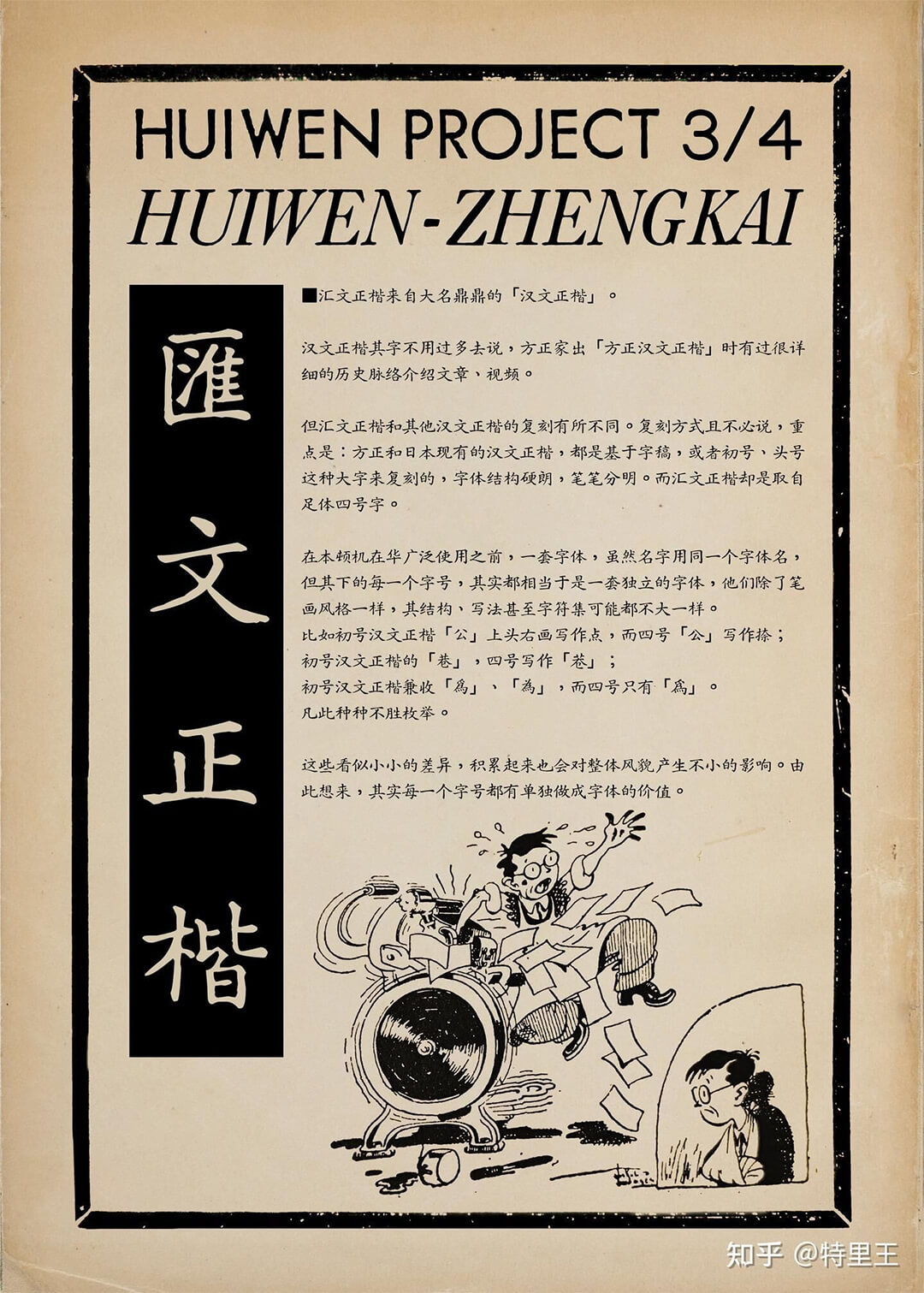
汇文正楷来自大名鼎鼎的「汉文正楷」。
汉文正楷其字不用过多去说,方正家出「方正汉文正楷」时有过很详细的历史脉络介绍文章、视频。
但汇文正楷和其他汉文正楷的复刻有所不同。复刻方式且不必说,重点是:方正和日本现有的汉文正楷,都是基于字稿,或者初号、头号这种大字来复刻的,字体结构硬朗,笔笔分明。而汇文正楷却是取自足体四号字 。
在本顿机在华广泛使用之前,一套字体,虽然名字用同一个字体名,但其下的每一个字号,其实都相当于是一套独立的字体,他们除了笔画风格一样,其结构、写法甚至字符集可能都不大一样。
比如初号汉文正楷「公」上头右画写作点,而四号「公」写作捺;初号汉文正楷的「巷」,四号写作「巷」;
初号汉文正楷兼收「爲」、「為」,而四号只有「爲」。
凡此种种不胜枚举。
这些看似小小的差异,积累起来也会对整体风貌产生不小的影响。由此想来,其实每一个字号都有单独做成字体的价值。